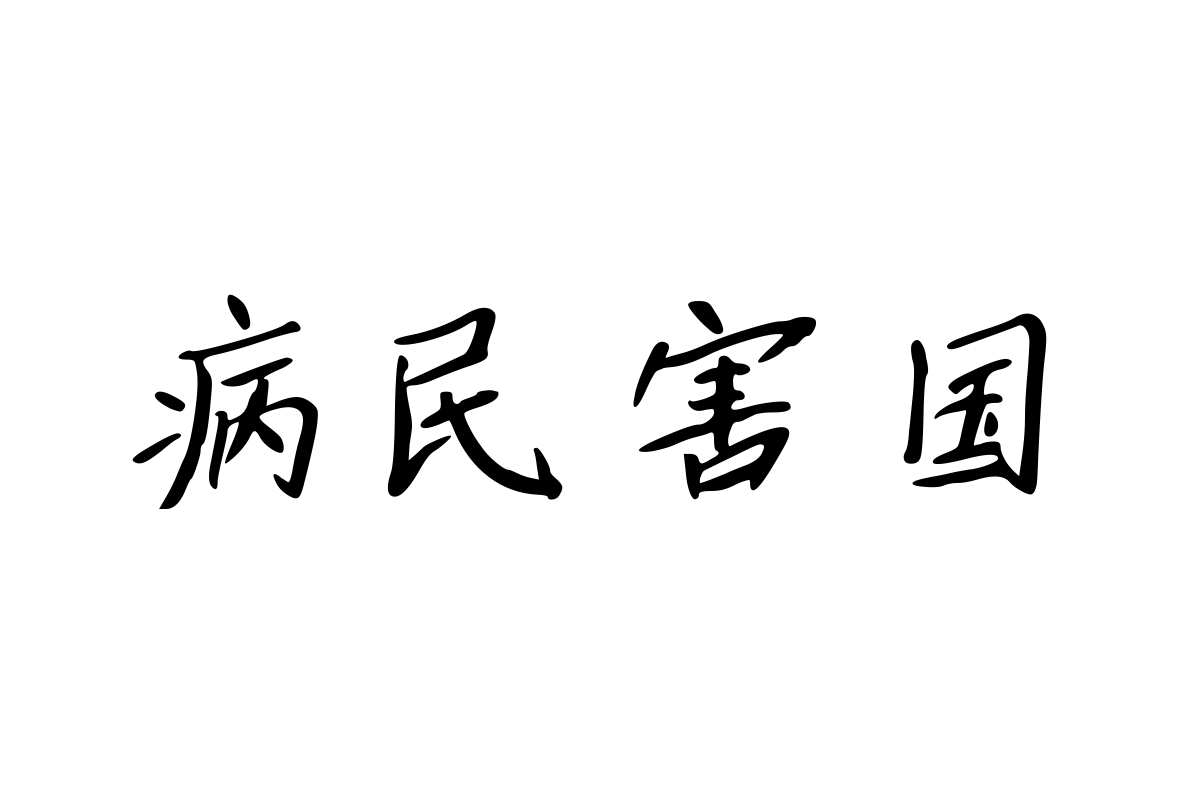
思雨岁月悠悠字体是一种具有独特韵味的书法字体,它的笔画流畅自然,结构严谨而不失灵动。这种字体给人一种宁静、优雅的感觉,仿佛让人置身于古代的山水之间,感受着岁月的沉淀和岁月的悠长。
思雨岁月悠悠字体的特点主要体现在以下几个方面:
1. 笔画流畅:这种字体的笔画线条流畅自然,没有过多的装饰和修饰,给人一种简约而不失美感的感觉。
2. 结构严谨:虽然笔画流畅,但整个字体的结构却非常严谨,每个字都保持着一定的平衡和对称,使得整个字体看起来既稳定又富有张力。
3. 灵动飘逸:这种字体在保持结构严谨的同时,也不失灵动飘逸的感觉。无论是横平竖直还是撇捺勾挑,都显得那么自然和谐,仿佛随时都可能随风飘动。
4. 意境深远:思雨岁月悠悠字体所蕴含的意境深远,仿佛让人置身于古代的山水之间,感受着岁月的沉淀和岁月的悠长。这种意境不仅体现在字体本身,更体现在使用者对这种字体的感知和理解中。
总之,思雨岁月悠悠字体是一种具有独特韵味和深厚文化底蕴的书法字体,它以流畅的笔画、严谨的结构、灵动的飘逸和深远的意境,为人们带来了一种独特的审美体验。